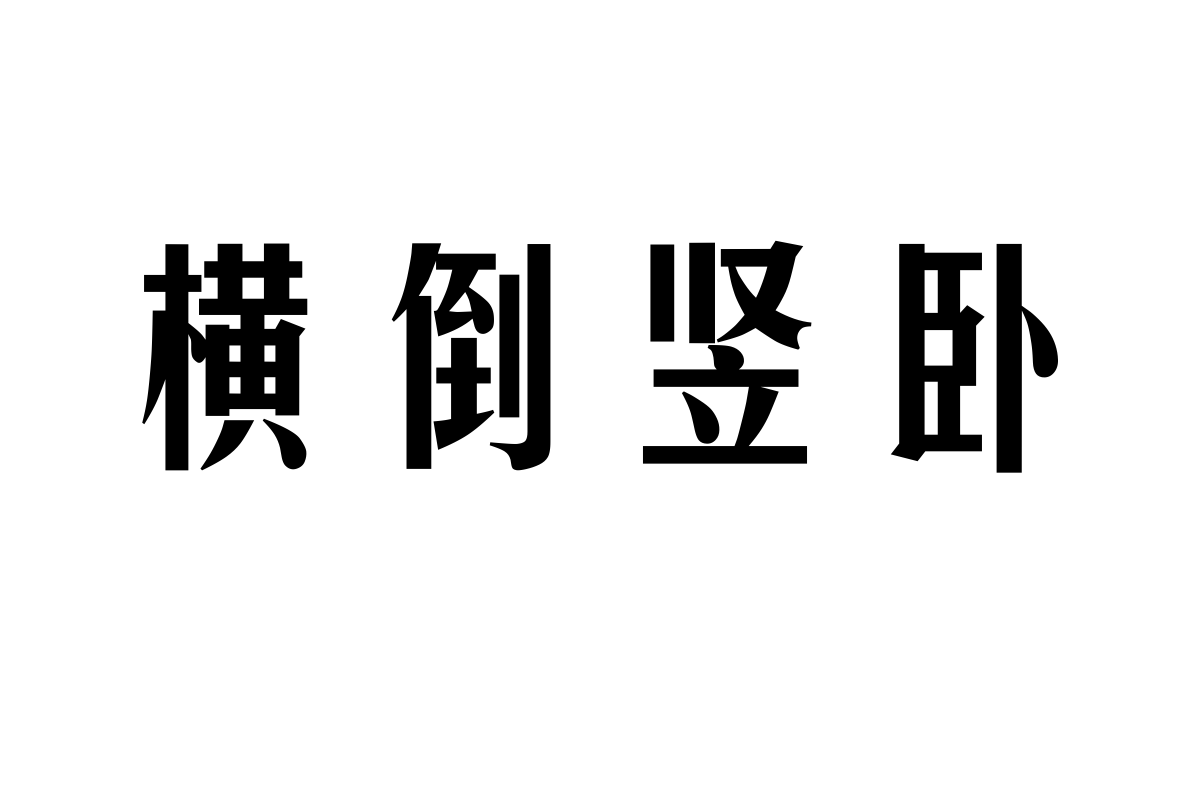
汉仪长美黑简是一款具有现代感的中文字体,其设计灵感来源于传统的书法艺术,但又融入了现代审美元素。这款字体线条流畅、结构紧凑,给人以简洁明快的感觉。
在字体大小方面,汉仪长美黑简提供了多种尺寸选择,以满足不同场景的需求。无论是用于标题、正文还是广告宣传,都能展现出独特的魅力。
此外,汉仪长美黑简还具备一定的可读性,适合用于需要清晰阅读的场合。同时,这款字体也具有一定的美观度,能够吸引读者的注意力。
总之,汉仪长美黑简是一款兼具现代感和美感的中文字体,适用于多种场景和需求。